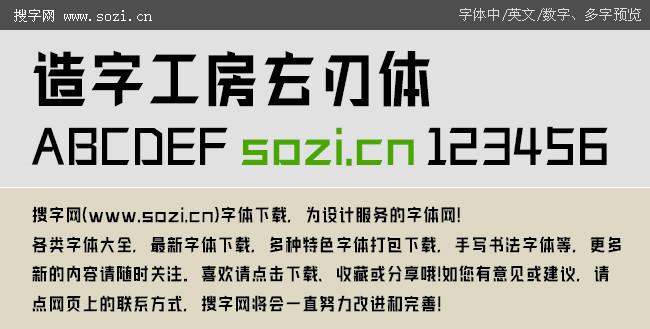
造字工房玄刃體
搜字網(wǎng)給大家提供一款造字工房玄刃體中文字體下載,造字工房玄刃體筆畫遒勁剛健,橫畫處作切角處理令其鋒芒畢露,更具剛毅果敢。結構疏密得宜,平整均衡,欹正相生,參差錯落,富有力量感和節(jié)奏感。適用于大標題、包裝設計、海報設計等應用。(本字體為個人非商用版,如需要商用請聯(lián)系官方購買版權)